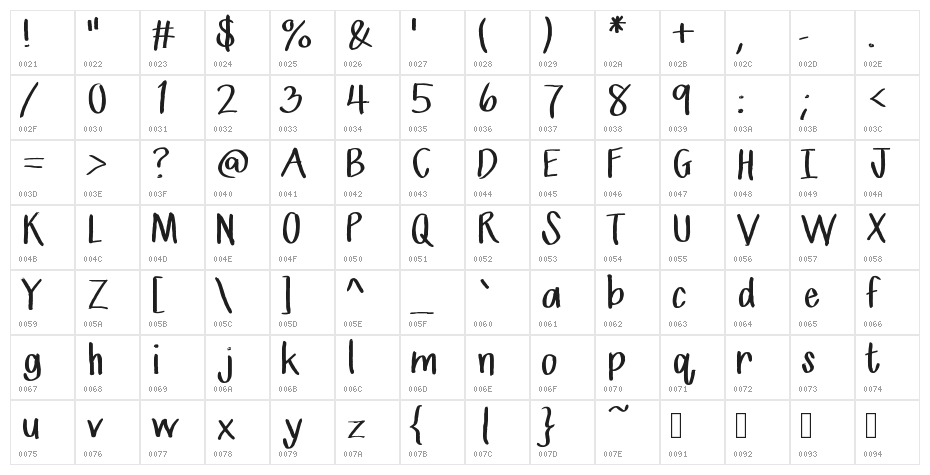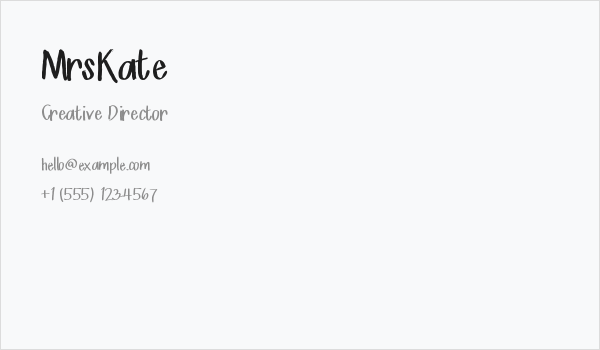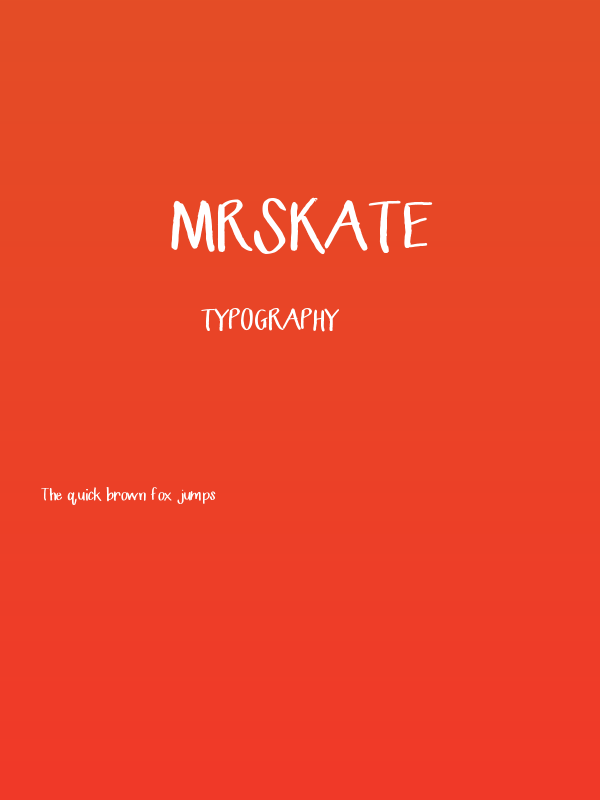
MrsKate Font
| Общий стиль | Casual, Playful |
| Область применения | Headlines, Logos, Creative projects |
| Рекомендуемые проекты | Ideal for greeting cards, invitations, personal branding, social media graphics, and creative projects that require a personal touch. |